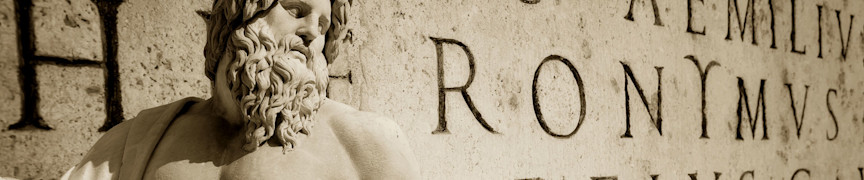
Wat is typografie? Alles over type en design in één infographic
Niets is zo bepalend voor het uiterlijk van je ontwerp als de keuze voor het lettertype. Strak, vriendelijk, uitbundig of modern: die uitstraling bepaal jij met de keuze voor je lettertype. Daarom is het goed om te weten hoe typografie werkt. Wanneer je de anatomie van een letter kent, weet je hoe je het beste lettertype kiest voor jouw doel. De basics leggen we je uit in deze infographic.